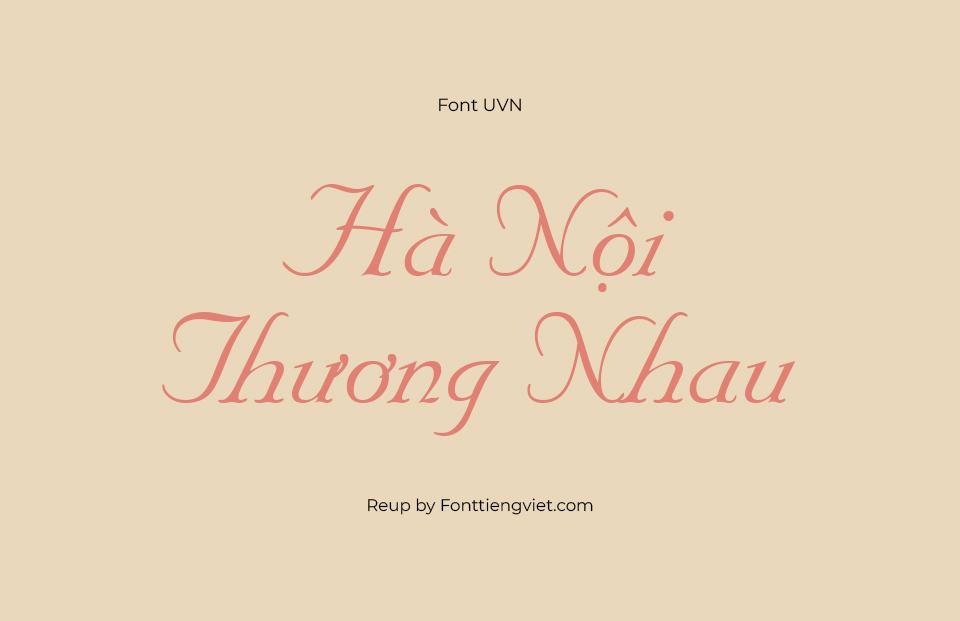
Font Việt Hóa UVN Dinh Hon
Khám Phá Vẻ Đẹp Truyền Thống Của Font Việt Hóa UVN Dinh Hon Cho Giáo Dục
Giới thiệu về Font Việt Hóa UVN Dinh Hon trong thiết kế học đường
Trong môi trường giáo dục, việc lựa chọn Font Miễn Phí phù hợp đóng vai trò quan trọng giúp truyền tải thông điệp một cách trang trọng và gần gũi. Font Việt Hóa UVN Dinh Hon là một trong những bộ phông chữ tiêu biểu thuộc bảng mã Unicode, được thiết kế đặc biệt để phục vụ nhu cầu soạn thảo văn bản tiếng Việt. Với phong cách thanh lịch và nét chữ rõ ràng, bộ font này không chỉ mang lại giá trị thẩm mỹ cao mà còn đảm bảo tính dễ đọc cho học sinh và giáo viên trong các bài giảng hay tài liệu học tập hằng ngày.
Đặc điểm nổi bật của Font Việt Hóa UVN Dinh Hon
Phong cách thiết kế và tính ứng dụng cao
Font Việt Hóa UVN Dinh Hon sở hữu đường nét hài hòa, kết hợp giữa yếu tố truyền thống và hiện đại. Các ký tự được chăm chút kỹ lưỡng, giúp tránh hiện tượng lỗi dấu tiếng Việt thường gặp ở các bộ phông ngoại nhập. Điều này cực kỳ hữu ích khi thiết kế bằng khen, giấy mời hoặc các bảng tin nhà trường. Ngoài ra, phông chữ này còn có độ tương phản vừa phải, giúp mắt không bị mỏi khi theo dõi các đoạn văn bản dài trên màn hình máy tính hoặc tài liệu in ấn.
Khả năng tương thích trên nhiều nền tảng
Lời kết về bộ font chữ độc đáo này
Việc sử dụng Font Việt Hóa UVN Dinh Hon giúp các sản phẩm thiết kế giáo dục trở nên chuyên nghiệp và mang đậm bản sắc Việt. Đây là lựa chọn lý tưởng cho những ai đang tìm kiếm giải pháp Font Miễn Phí, Font Việt Hóa, Font Việt Hóa UVN Dinh Hon chất lượng cao. Hy vọng bộ chữ này sẽ giúp bạn sáng tạo nên nhiều tài liệu học tập bổ ích và đẹp mắt.